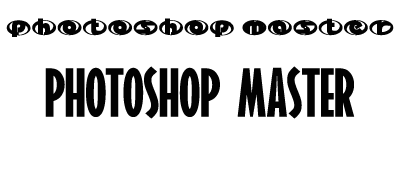
Шрифт-логотип прям. =)
Давно хотел такой шрифток...
ну вот только буржуйский...надо как-то отсортировать шрифты (русский и буржуйский) а то пока не откроешь не увидишь :(
классный шрифт